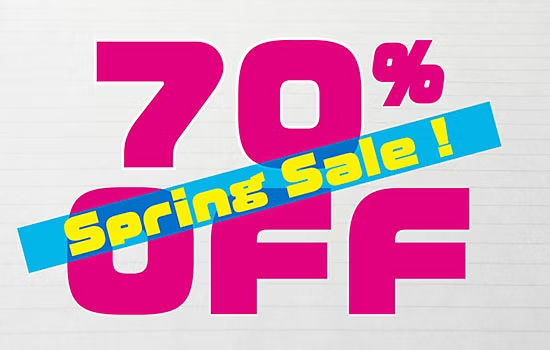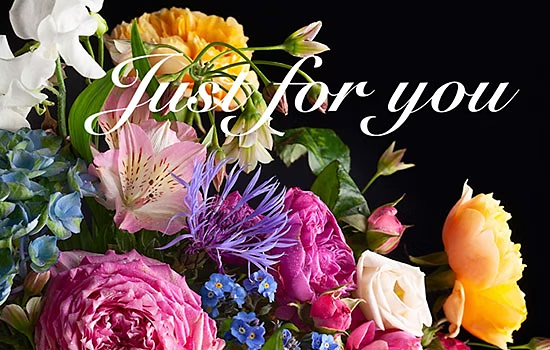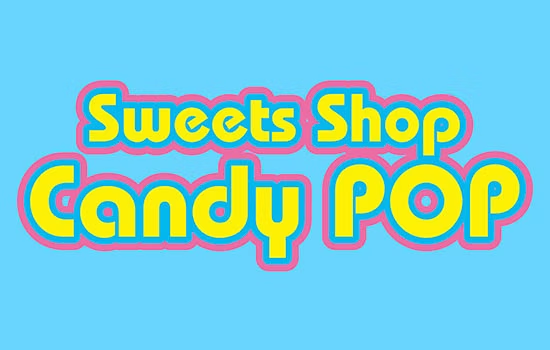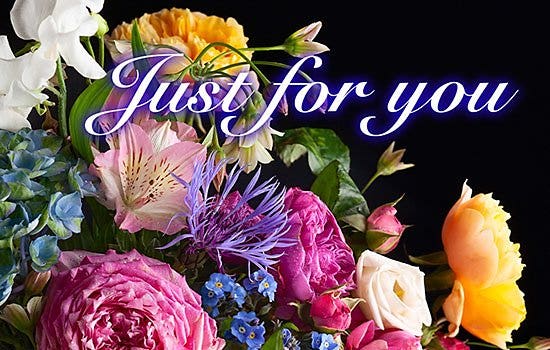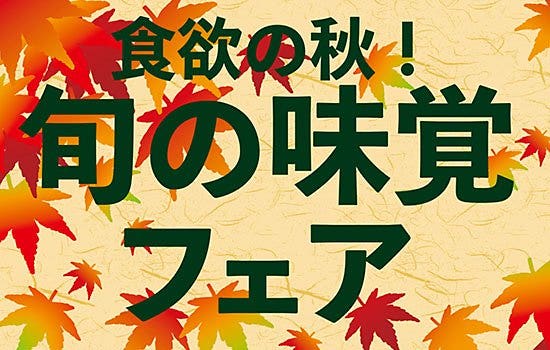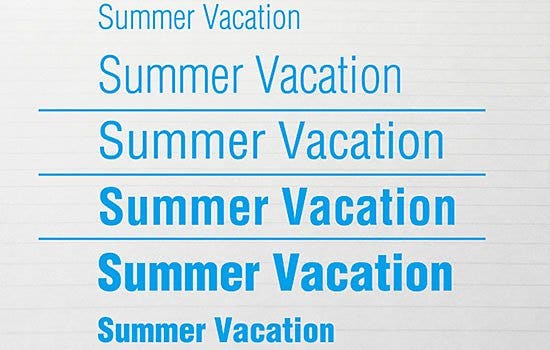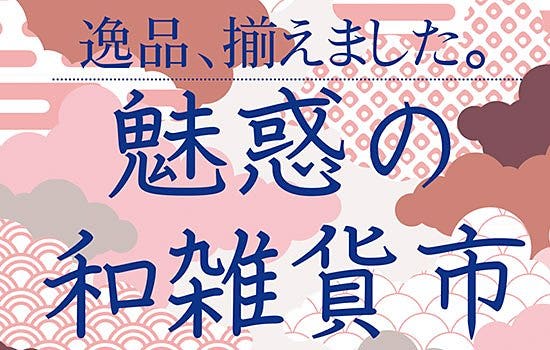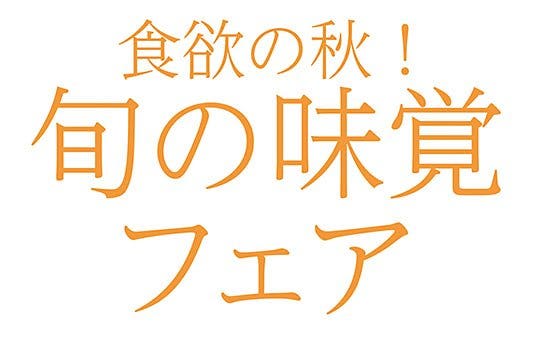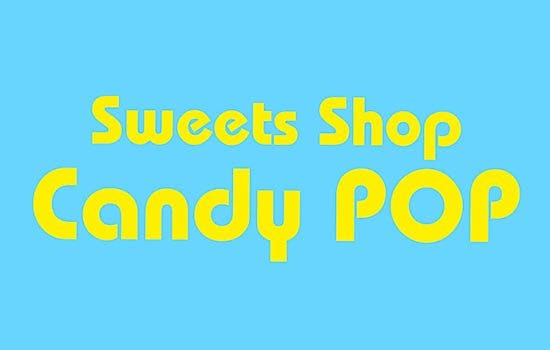
タイトルや見出しに向く、見やすいフォントの選び方
フォントには用途に合わせてさまざまな種類があります。
雑誌や書籍のように長文に向くものもあれば、パッと見のインパクトを重視したディスプレイ用の書体、あらゆる人にも見やすい、読みやすい、見間違えにくいことを重視したUD書体など、実に多種多様なものが用意されています。
ここではタイトルや見出しに向く、視認性の高いフォントの選び方、考え方について紹介します。
読みやすいフォントとは?
読ませる文章に向くフォント、つまり読みやすいフォントとはどのようなフォントなのでしょうか。
日本語は一般的に、漢字とかなを中心に「、」「。」などの約物を組み合わせて文章を作ります。このとき、漢字はおもに意味を伝える役割を担い、かなはそれを補うかたちで構成されると考えられており、漢字とかなの間に適度なメリハリをつけることが、読みやすさを考えるひとつのポイントになります。
細いフォントの例
太いフォントの例
明朝体、ゴシック体、丸ゴシック体のように、本文でも使えるタイプの太いフォントでも十分、タイトルや見出しに使えますが、より人目を引く、キャッチーなかたちの見出し用デザインフォントも多くリリースされています。
太い、文字の大きい、インパクトのあるフォント
タイトルや見出しだからといっても、太ければよい、文字が大きければよいというわけではありません。
見出し用として作られているフォントの多くは、太くても見やすい、読みやすいデザインになっていますが、重要なのはその使用するサイズです。線を太くすればするほど、必然的に文字をその文字と認識するために必要な文字内の空間は狭くなってきます。
このため、見出し・タイトルだからといって小さいサイズでやみくもに太いフォントを使ってしまうと、かえって見にくくなるということが起こりかねません。デザインするものの物理的なサイズに応じて、最適な太さのフォントを使うことが大切です。
レイアウトサイズによって適切な太さを選ぶことが重要です
細いフォントを大きくレイアウトした例
一方、大きなサイズで文字を配置できる場合には、大きさゆえに目の引きやすいとも言えるので、あえて細めのフォントですっきりと仕上げるということも可能になります。
レイアウトや周りの要素とのバランスの中で、最も読みやすい太さとかたちを探っていくことがデザインでは重要です。
見やすさ、伝わりやすさはフォント+デザインで決まる
太いフォント、文字の大きいフォントの多くは見出し用に設計されていますが、こうしたフォントを使えば必ずしも人目を引く、見やすい文字になるとは限らないのは前述の通りです。見やすさ、伝わりやすさは適切なフォントの選択とデザインのバランスによって決定されます。
たとえば、込み入った絵柄の写真の上に文字を置く場合には太いフォントの方が読みやすいと言えますし、余白が十分に取れている場合には細いフォントでも見やすさは十分に保たれます。
地とのコントラストが十分な場合、細いフォントでも十分読みやすさは保たれます
地に絵柄や写真がある場合は、太いフォントを使ったほうが読みやすくなります
文字と文字の間隔(字間)、行と行の間隔(行間)の取りかたによっても印象は変わります。
字間・行間を詰めて、見出し・タイトルの文字にカタマリ感を出すと、それだけで見出しと認識しやすい文字の強さが生まれますし、あえて字間を広くとることで見出し・タイトルスペースを大きく取り、見出しとして認識できるようにするという手法もあります。
太いフォントをそのままレイアウトしたもの
字間を調整してカタマリ感を出したもの
次項目からは、フォントの文字を配置しただけではなく、ちょっとした加工、デザイン処理によって、より見やすい、伝わりやすい見出し・タイトルに変えていく手法について紹介していきます。
文字を見やすくする加工例[1]フチ文字
見出し・タイトル向けの加工としてよく知られているのが文字の周りに線をつけるフチ文字加工です。フチは一重だけでなく、二重、三重に重ねてつけることもあります。
フォントの文字そのままの状態
二重にフチをつけたもの
フチ文字加工は一重であれば、AdobeIllustrator・AdobeInDesignともに文字に線を設定し、 線を輪郭の外側に設定するだけで作ることができます。
二重、三重のフチ文字にする場合には、太い線幅の文字を重ねるか、Illustratorの「アピアランス」を活用し、ひとつのテキストオブジェクトに対して、線を重ねていくことで簡単に作れるようになっています。
文字を見やすくする加工例[2]ドロップシャドウ
文字に影をつける「ドロップシャドウ」も、見出し・タイトル向けによく使われる加工です。
ドロップシャドウをつけた文字は、文字自体に立体感が生まれ、その他のデザイン要素に比べて、ひとつ上のレイヤーにあるように見えるようになります。これによって、文字が他の要素に対して手前に見えるようになり、結果として目を引くという効果が生まれます。
フォントの文字そのままの状態
ドロップシャドウをつけたもの
ドロップシャドウは、Illustratorでは「効果」メニューの「スタイライズ」から、InDesignでは「オブジェクト」メニューの「効果」(または「効果」パネル)から簡単に設定することができます。
文字を見やすくする加工例[3]光彩
ドロップシャドウに似た効果ですが、同じようにタイトル等に使われる加工が「光彩」です。
ドロップシャドウがオブジェクトに光を当て、その影をつけるような加工に対し、「光彩」はオブジェクトそのものが光を放っているような効果を持たせるものです。「光彩(外側)」、「光彩(内側)」の2種類があり、それぞれオブジェクトの外側に向かって光を放つか、内側に向かって放つかが決まります。
光彩、特に光彩(外側)がよく使われるシチュエーションは、背景が複雑な写真やイラスト、テクスチャの場合です。文字に対して光彩(外側)を適用することで、文字の輪郭がクリアになり、よりその文字が認識しやすくなるという効果があります。
フォントの文字そのままの状態
光彩(外側)を設定したもの
光彩は、ドロップシャドウ同様、Illustratorでは「効果」メニューの「スタイライズ」から、InDesignでは「オブジェクト」メニューの「効果」(または「効果」パネル)から設定します。